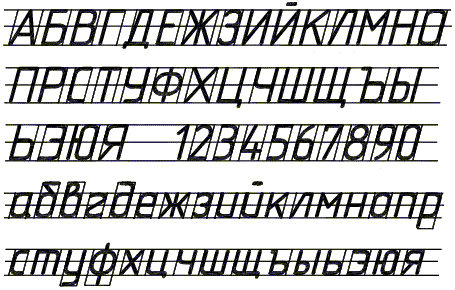
Шрифты чертежные. На чертежах и других конструкторских документах всех отраслей промышленности и строительства применяют чертежный шрифт
На чертежах и других конструкторских документах всех отраслей промышленности и строительства применяют чертежный шрифт, который устанавливает ГОСТ 2.304— 81 (СТ СЭВ 851— 78—СТ СЭВ 855—78). Размер шрифта определяется высотой прописных букв в миллиметрах. Высота букв h измеряется перпендикулярно к основанию строки. Высота строчных букв с определяется из отношения их высоты (без отростков) к размеру шрифта h, например для шрифта типа А высота с= 10/14h, а для шрифта Б высота С=7/10h. Ширина буквы g определяется по отношению к размеру шрифта, например для шрифта типа А размер g=1/2h, а для типа Б размер g=6/10h, или по отношению к толщине линии шрифта d, например для шрифта типа А ширина буквы равна 7d (для широких букв 9d), а для шрифта типа Б ширина буквы равна 6d (для широких букв 8d). Толщина линии d определяется в зависимости от типа и высоты шрифта: для типа А размер d=1/14h; для типа Б размер d=1/10h. Для освоения написания шрифта рекомендуется использовать вспомогательную сетку, рис. 2.
Рис. 2 – Вычерчивание букв и цифр по вспомогательной сетке.
Рис. 3 – Шрифты чертежные. Для выполнения надписей на чертежах рекомендуется шрифт типа Б с наклоном 75о. В табл. 1 приведены параметры этого шрифта. Образец букв и цифр шрифта типа Б дан на рис. 3.
Таблица 1 – Размеры параметров шрифта типа Б